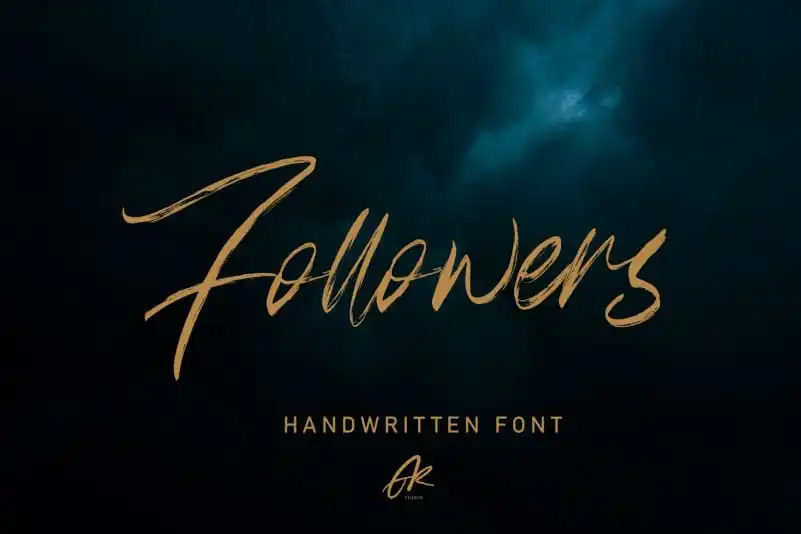
Aqui está uma versão curta e envolvente para a página de download da Font ‘Follower Brush’, baseada nas descrições dadas: A Follower Brush é uma tipografia realista criada pela arendxstudio, com um traço genuíno produzido por pincel. Oferece diversas alternativas, ligaturas e swashes para adaptar a fonte à sua necessidade de design. Perfeita para aplicação em títulos, como etiquetas de roupa ou cartas, design de livros, identidades visuais, assinatura de marca ou até mesmo em embalagens, impressões de fãs e materiais publicitários. Feitas especialmente para quem aprecia o resultado natural da arte digital sobre papel, estas características tornam a Follower Brush uma ótima opção para designers que desejam um toque autêntico e criativo em suas criações. Seja você um aspirante ou um profissional, certamente encontrará neste design uma opção versátil e inspiradora para seus projetos. Além disso, a Follower Brush oferece tanto letras A-Z quanto numerais e pontuação (Standard OpenType), além de suporte aos acentos e caracteres multilíngues. As ligaturas são outra característica destacada da fonte, garantindo uma experiência visual fluida para aqueles que trabalham com textos mais longos. Não perca tempo – experimente esta arte digital de primeira linha em seus próximos projetos! Seja um seguidor ativo e deixe-nos saber o que você acha. Comentários, elogios e sugestões são sempre bem-vindos.